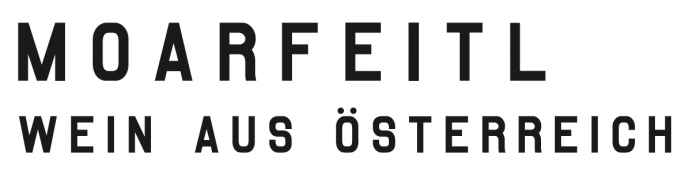
Technischer Font auf Wein-Etikett
ich hab diese Schrift auf einen Weinetikett entdeckt und würde sehr gerne wissen, wie dieser Font heißt. : )
Ich weiß es nicht, hätte aber noch ein paar Buchstaben, vielleicht erleichtert das die Suche. Die Vektoren sind im pdf.
:tutor:  Da irrt wtf aber, weil die Noasarck ganz andere Proportionen hat.
Noarsack:
Puhhh, danke für die Tipps. Myfonts und What the font Suchmaschine geben leider keine korrekten Ergebnisse aus.
Norsack kommt den ganzen nahe, aber trotzdem noch zu weit weg.